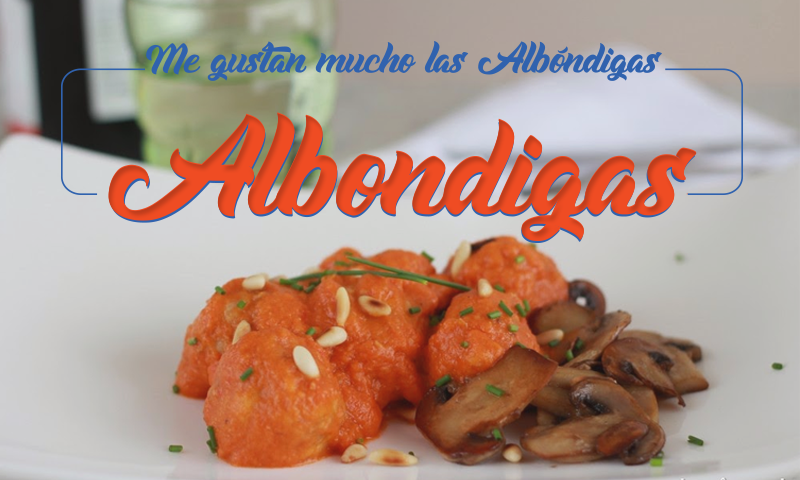
Albóndigas Script Font – Download Grátis
A Albóndigas Script Font é uma elegante escolha para designers buscam transparência e sofisticação em seus projetos. Seu design curvilíneo e fluido canta um sussurro de conforto, sendo perfeito para títulos de página ou letras quebradas nas peças gráficas. Este script não é apenas atraente, mas também tem uma funcionalidade robusta para garantir que sua fidelidade ao trabalho seja preservada mesmo em formatos de mídia digitais mais exigentes. A Octotype Designer criou algo definitivamente singular e irresistível para aqueles que buscam um estilo refinado e elegante. Com licenças comerciais disponíveis, designers podem experimentar a beleza da Albóndigas Script Font sem restrições, permitindo-lhes explorar suas infinitas possibilidades em designs de marca ou publicações digitais. Não perca essa oportunidade para revolucionar o aspecto visual de seus projetos com este font único e intrigante. Aproveite a experiência desta fonte para transmitir uma mensagem através da forma e do conteúdo, deixando um impressionante sabor na memória dos seus destinatários.